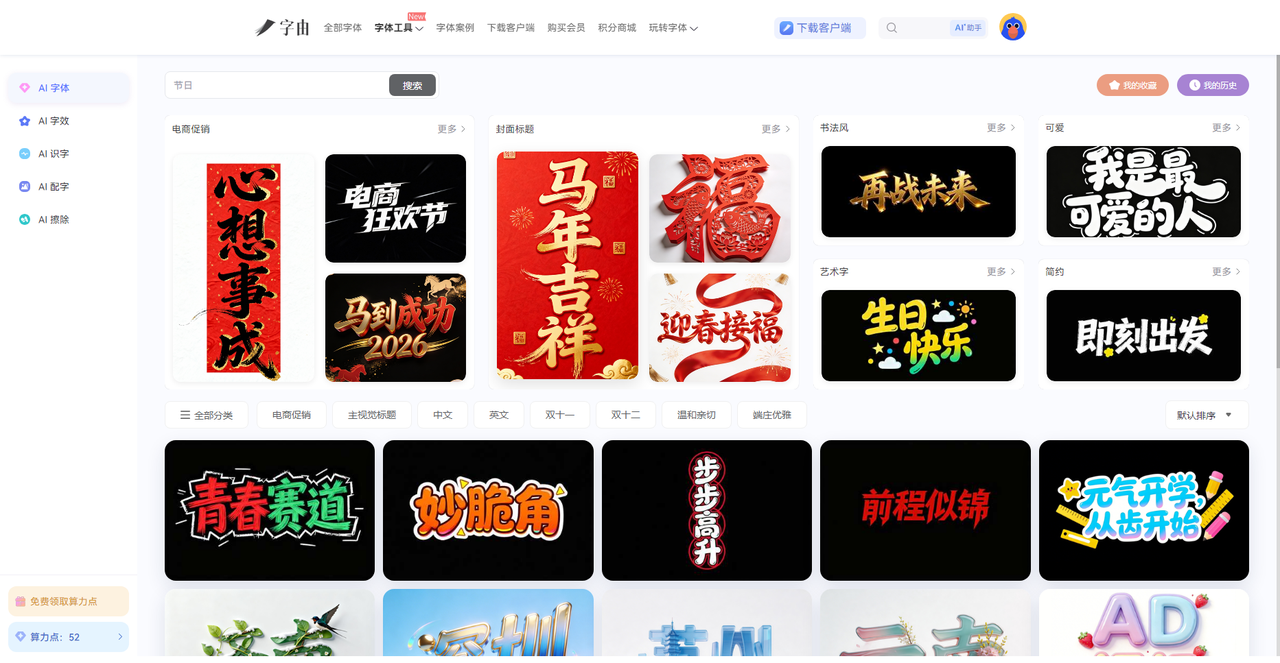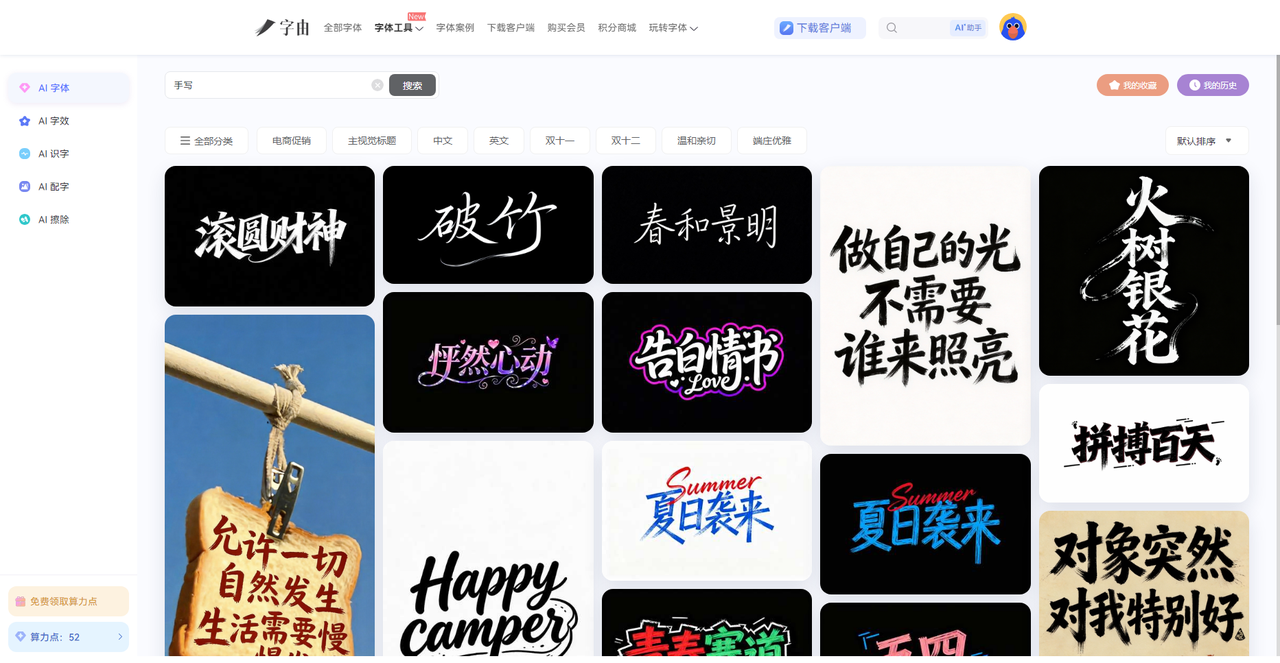
想要手写感字体?试试这几个手写字体生成器
你有没有过这种经历:做手账的时候,想写一段漂亮的标题,结果自己写出来的字歪歪扭扭;做贺卡的时候,想要那种手写质感,却找不到合适的字体;发朋友圈想配一句话,系统自带字体又太生硬。其实,想要手写感字体,根本不用自己练字,也不用到处搜字体包。现在有专门的手写字体生成器,输入文字,选个风格,几十秒就能拿到一张逼真的手写体图片。今天我就重点介绍一个我用着最顺手的工具——字由,再顺便分享几个其他的好用的工具。需要的直接收藏。
很多人知道字由是字体库,上万款字体可以使用。但很多人不知道,字由的“AI字体”功能,本身就是一款超级好用的手写字体生成器。你不需要下载任何字体,也不用装软件,打开网页就能用。
如果按照以前来看,想要手写感字体,你得先去字体网站翻,找到一款手写体,下载、解压、安装,然后打开PS,打字,看效果。如果不满意,再重复一遍。光试字体就能耗掉半天。更麻烦的是,很多手写体字体有版权问题。你辛辛苦苦做完的设计,万一字体不能商用,全白干。
字由的AI字体功能,把“找手写体”变成了“选手写模板”。你不用下载任何东西,直接在网页里输入文字,选一个手写风格的模板,点一下生成,几十秒就出图。而且生成的是透明背景的PNG,直接拖进PS、剪映、Canva里就能用。
下面我会具体教大家怎么用字由的AI字体来生成手写体:
- 第一步:打开字由官网(hellofont.cn),在导航栏找到【字体工具】→【AI工具】→【AI字体】。不用下载客户端,网页版就能用。
- 第二步:进入页面后,你会看到很多模板。在搜索框里输入“手写”,系统会自动筛选出所有手写风格的模板。比如“手写体”“毛笔字”“钢笔字”“儿童手写”“浪漫花体”……几十种风格摆在你面前。
- 第三步:每个模板都有预览图,鼠标放上去就能看到效果。你可以先挑两三个看着喜欢的,收藏下来。
- 第四步:点进一个模板,点击“做同款”。在输入框里填你想生成的文字,比如“春日来信”“见字如面”“生日快乐”。注意:最好和模板的字数保持一致。模板是四个字,你就填四个字;模板是两个字,你就填两个字。这样生成的效果最自然。
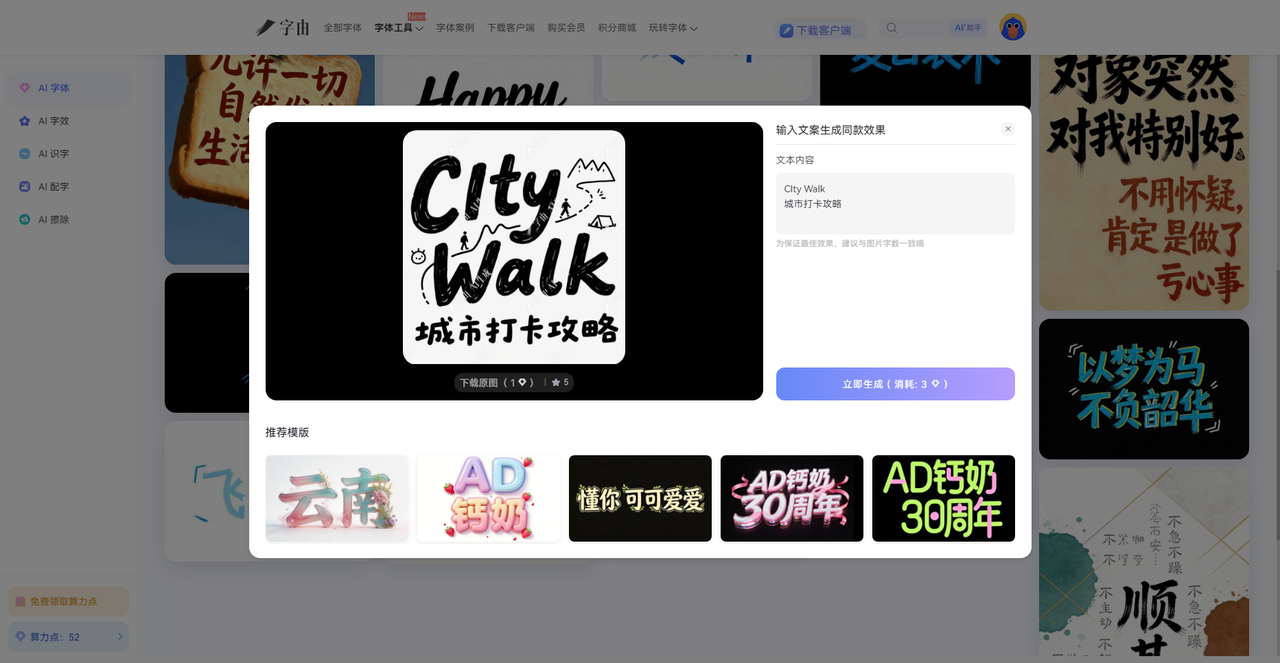
- 第五步:确认文案后,点击“立即生成”。等20-30秒,系统就会输出一张高清的手写艺术字图片。生成后可以预览,不满意就换其他模板再试。
- 第六步:生成满意后,点击下载。下载时有两个选项:带背景的可以直接用,透明背景的更方便后期排版。我一般选透明背景,直接拖进PS或者剪映里,不用抠图,不用调色。
除此之外,每个模板都不只是字体,而是带笔触、带墨韵、带纸张纹理的完整设计。你选好模板,换成自己的文案,生成的就是一张可以直接用的图。
在这方面,字由有很多的优点:
- 打开网页就能用,生成完就能下载。不像某些工具还要注册、登录、下载客户端。
- 透明背景PNG,分辨率够用,印刷、网络都能用。而且模板更新快,新出的手写风格很快就能在字由里找到。
- 生成之后直接拖进PS、AI、剪映,不需要二次处理。如果你装了字由客户端,还能一键应用到设计软件里。
如果你不想要特效,只是想用现成的手写体,字由的免费商用字体库里也有几百款手写体,随便挑。
所以,如果你想要手写感字体,字由是我最推荐的工具。不用下载,不用安装,不用怕版权。输入文字,选个模板,点一下,几十秒就出图。而且它不只是生成器,更是一个完整的手写字体解决方案。
2、Cursive Text Generator
这个工具叫Cursive Text Generator,
它不生成图片,而是把普通文字转换成各种花式手写字体,然后让你直接复制粘贴。打开网页,在输入框里打字,下面会列出十几种手写风格的字体预览,比如“ABC Unicode Script”“ABC Dancing Script”“ABC Lucida Handwriting”等。你可以调整字体大小和颜色,还能选透明背景。点击“Copy”按钮,就能把转换后的文字复制到剪贴板。直接去微信、微博、Instagram 粘贴,不用保存图片。适合做社交媒体文案、评论区签名、个性昵称。它还有专门针对Google Docs和MS Word的字体选项,如果你在用这些软件写东西,可以直接套用。
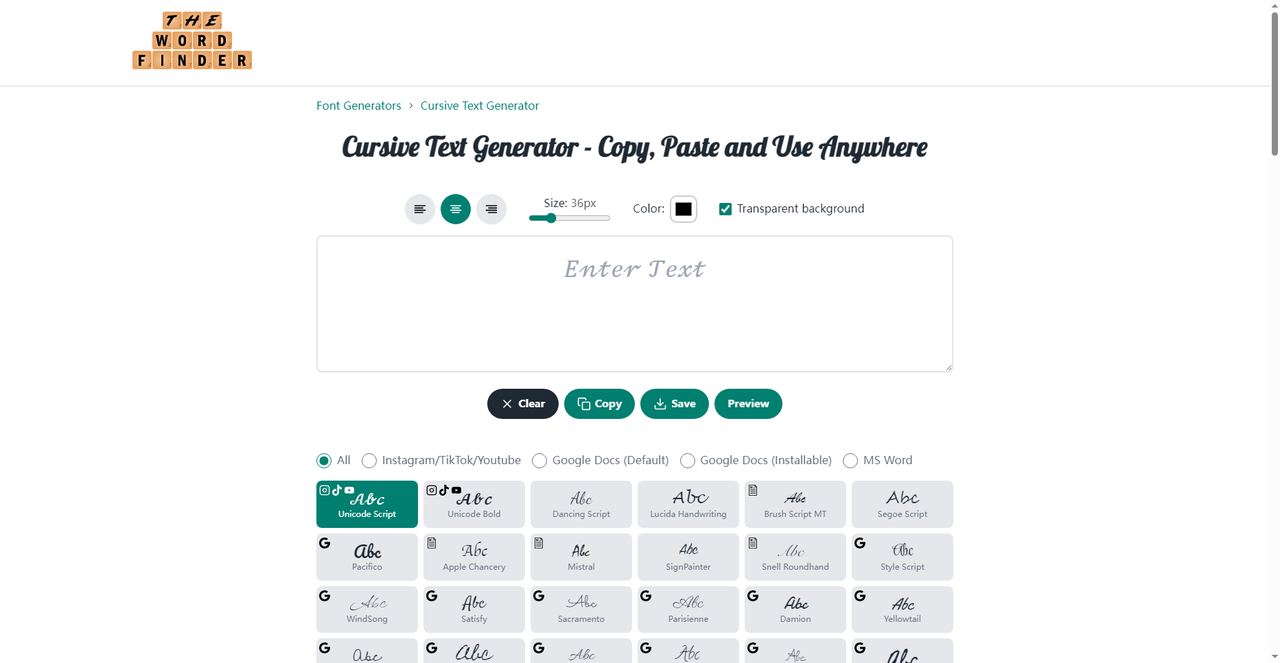
3、Handwriting Fonts
这个网站提供了120种手写字体样式。输入文字后,它会用各种手写体展示效果。每个样式旁边标注了“可读性”,比如“High Readability”(高可读性)、“Medium Readability”(中等)、“Low Readability”(低),如果你不确定哪种风格合适,可以按可读性筛选。做正文内容选高可读性,做装饰标题可以选低可读性。这个细节很贴心。
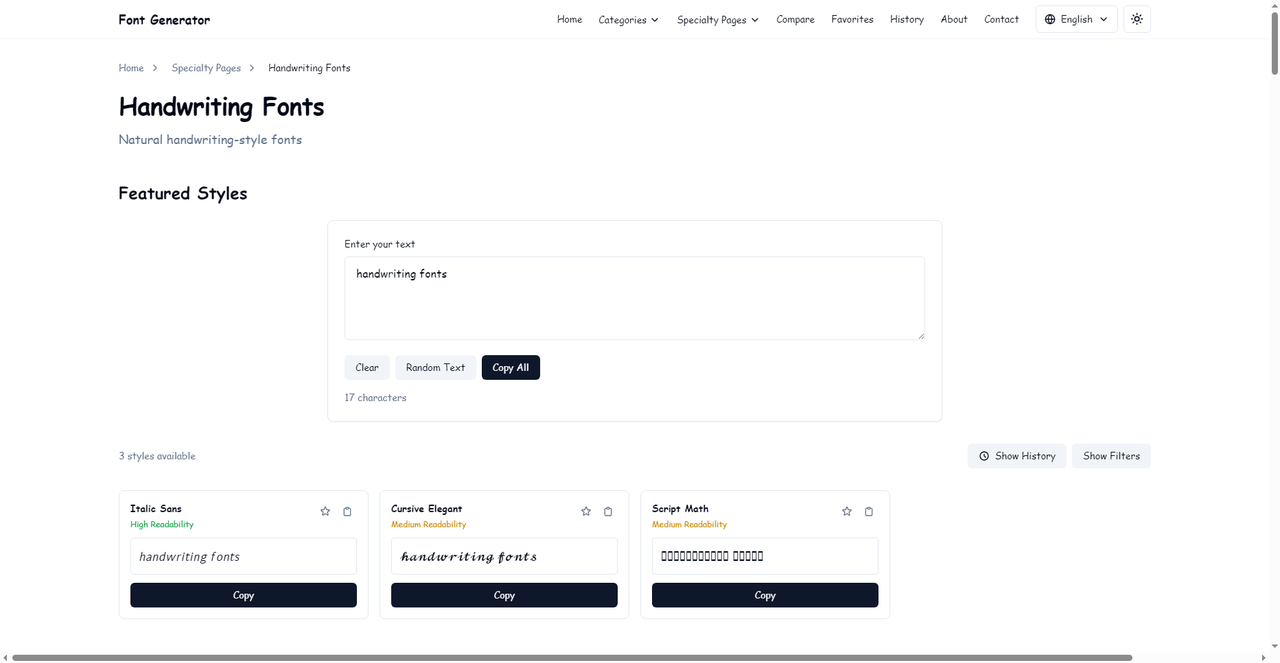
4、Text to Handwriting Converter
这个工具来自100L5,专门用来把文字转换成逼真的手写文档。它不像前面几个只生成一行字,而是可以生成整页的手写内容。适合做手写笔记、作业、信件、证书等。它模拟了真实手写的效果,有墨迹深浅和纸张纹理,看起来很像真的手写。
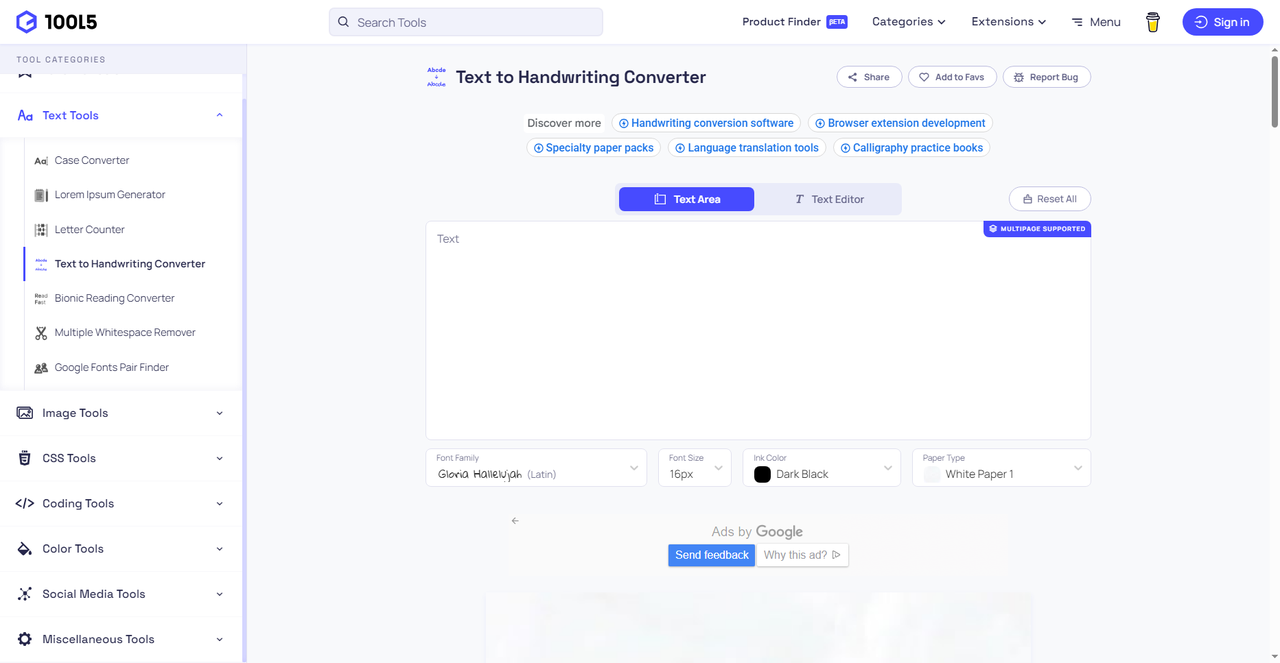
5、Handwriting Font Generator
这个工具功能很全面。输入文字后,点击“Generate Handwriting Samples”,它会一次性生成多种手写风格的预览,比如“Elegant Cursive”“Neat Handwriting”“Childish Writing”等。它还提供了“随机文本”功能,不知道写什么的时候点一下,自动生成示例文字。另外还有历史记录,你之前生成过的样式会保存下来,方便下次再用。
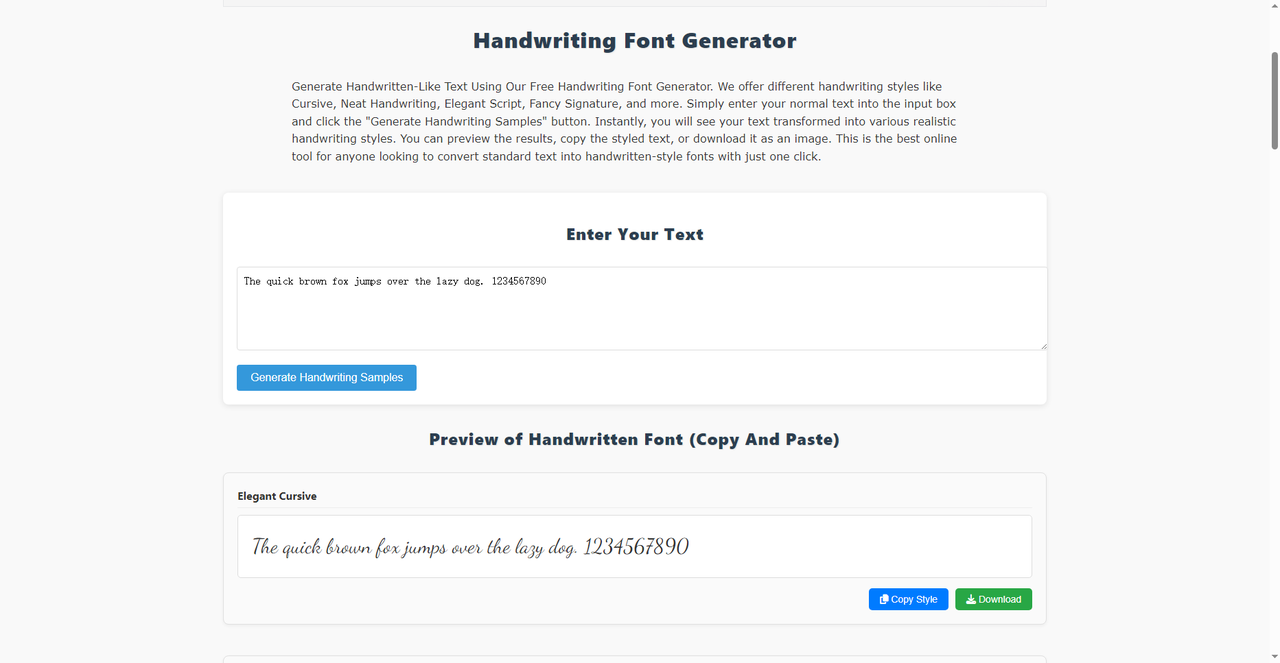
这几个手写字体生成器用起来都很不错,但是其中字由是我用的最多的,因为它既能生成手写艺术字,又能提供海量免费商用字体,还能一键应用到设计软件里。而且完全免费,没有水印,不用担心版权。再加上除了AI字体以外的其他AI工具也都很实用。如果你也想要手写感的文字,不妨从字由开始试试。打开网页,搜“手写”,选个模板,填上字,几十秒就可以拥有了。